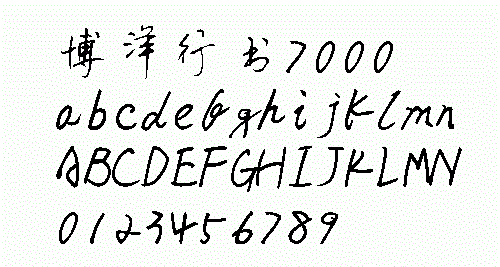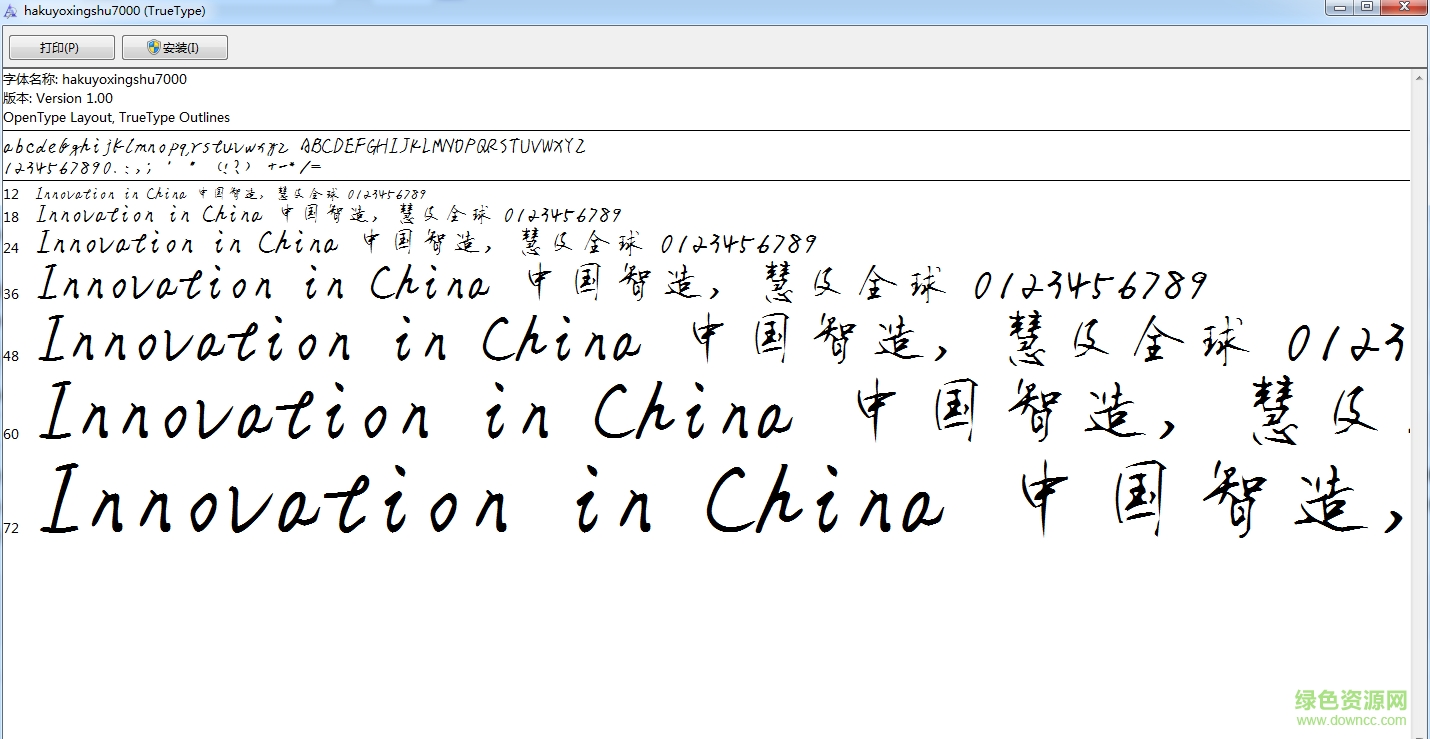
hakuyoxingshu7000 普通體
hakuyoxingshu7000又稱博洋行書(shū)7000字體,是一款灑脫漂亮的行書(shū)字體,線若游絲,撇捺舒展,筆畫(huà)飛揚(yáng),需要的朋友快來(lái)綠色資源網(wǎng)下載收藏吧1
行書(shū)字體介紹
行書(shū)是介于楷、草間的一種書(shū)體。寫(xiě)得比較放縱流動(dòng),近于草書(shū)的稱行草;寫(xiě)得比較端正平穩(wěn),近于楷書(shū)的稱行楷。